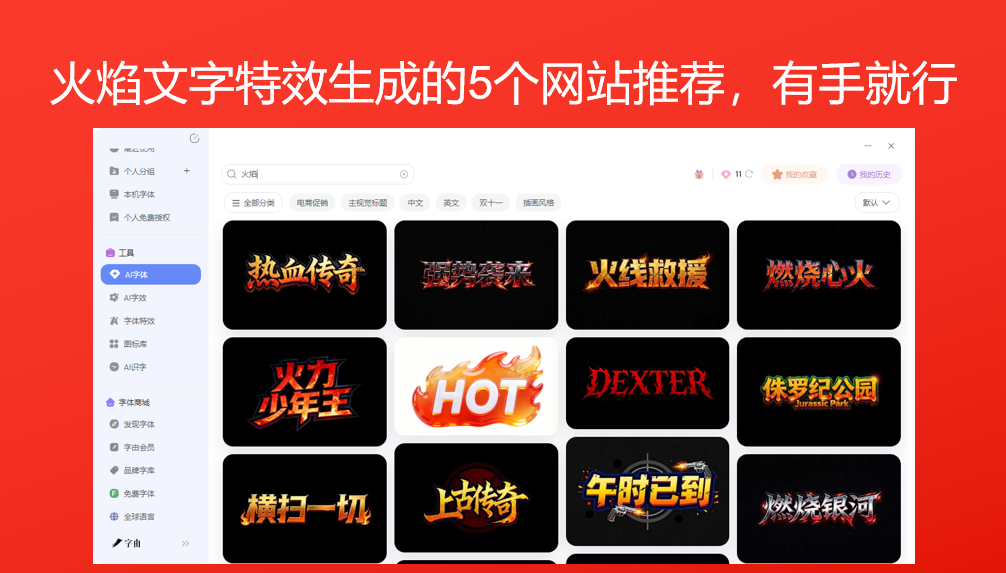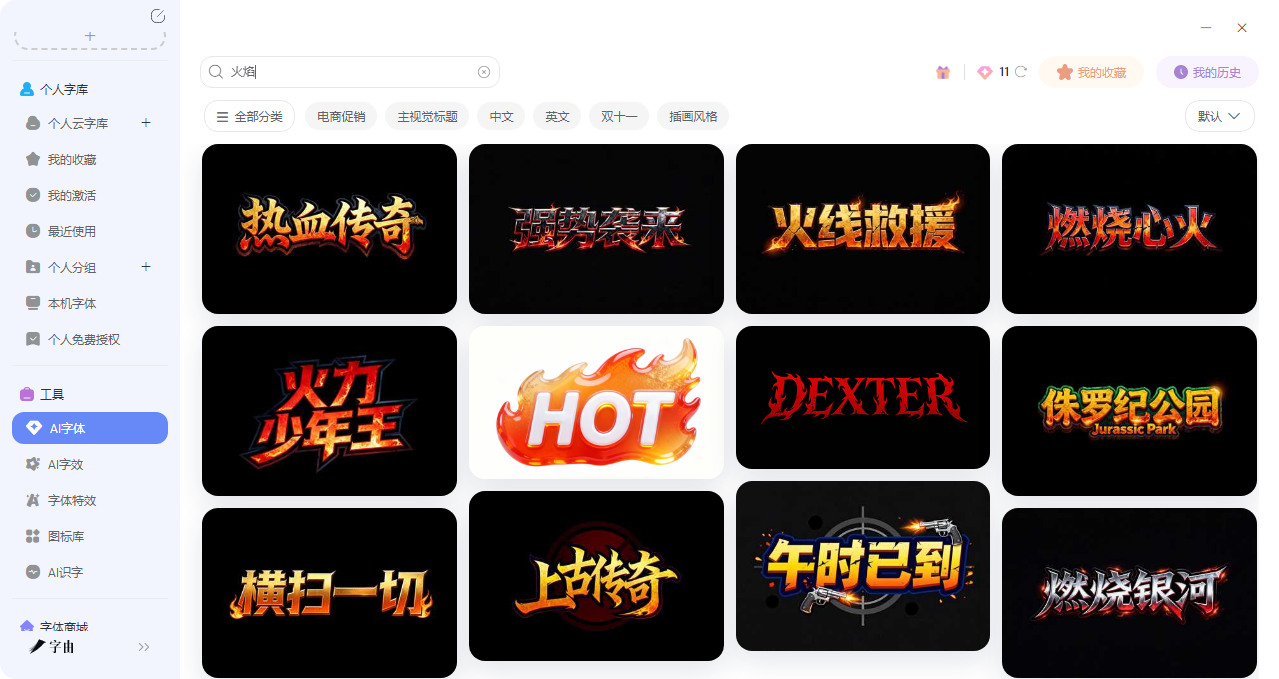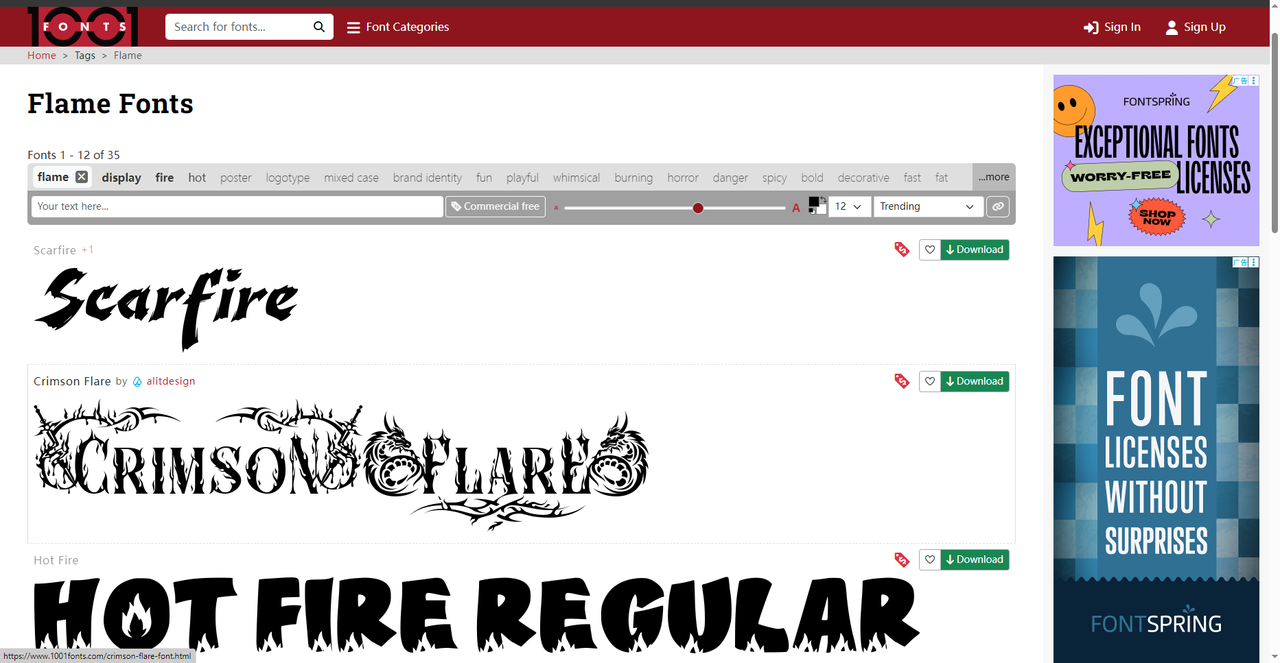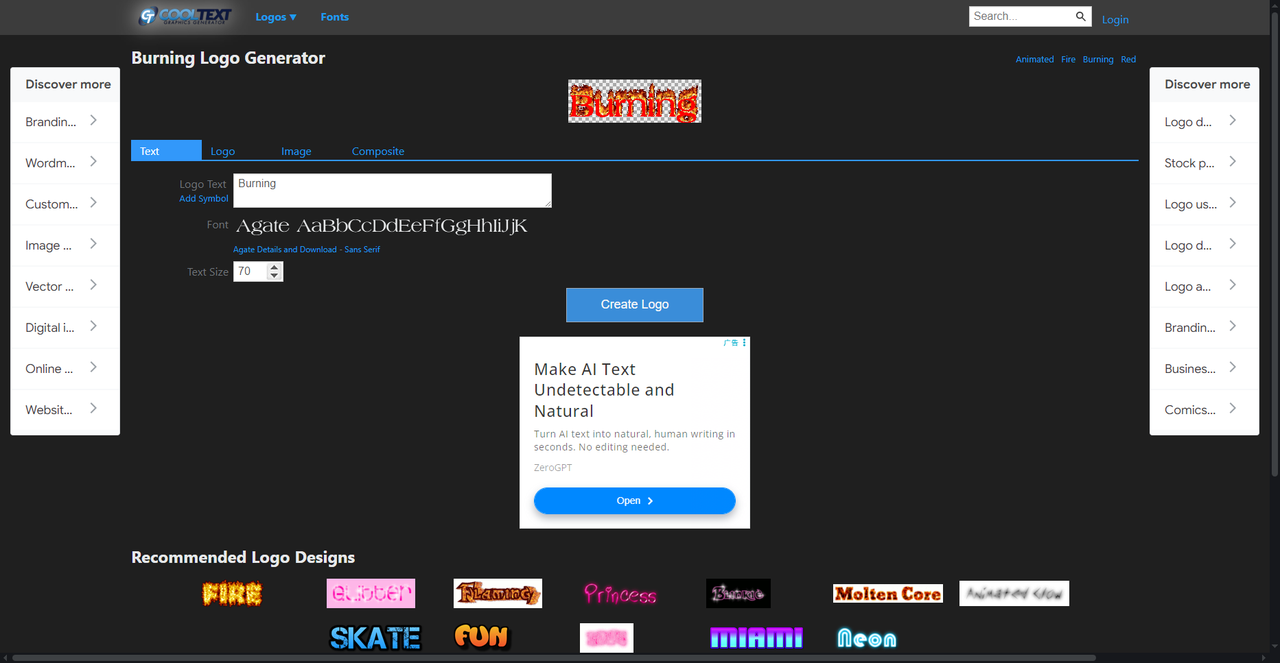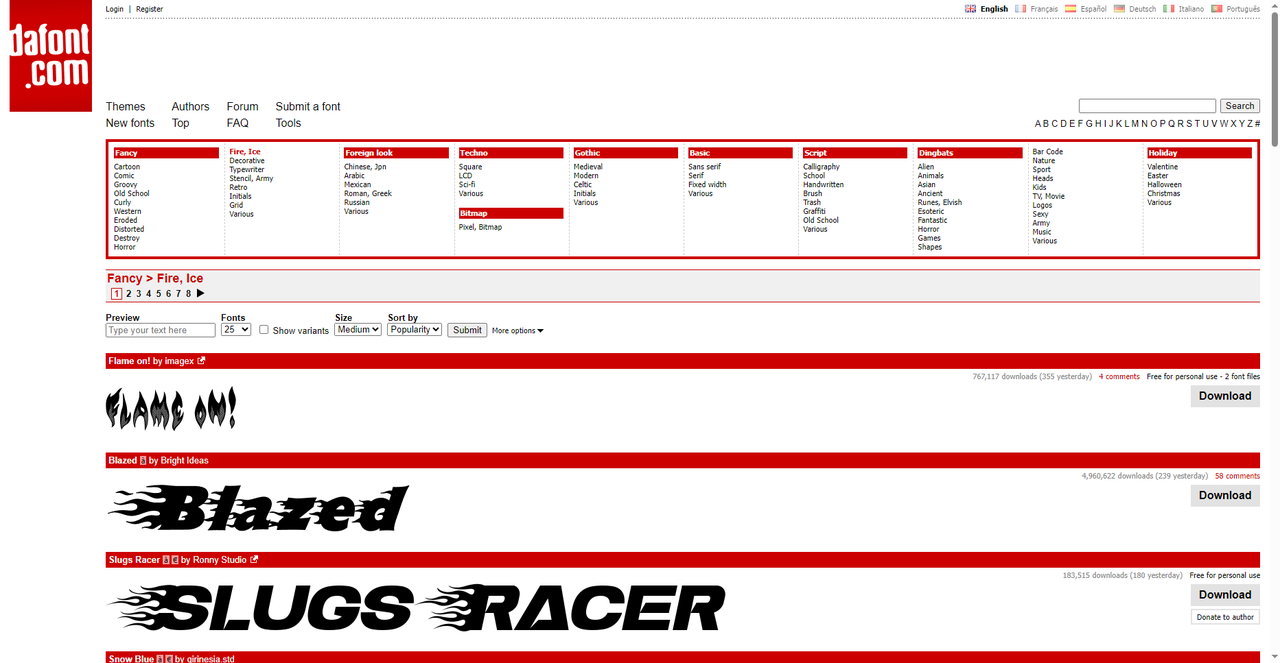
火焰文字特效生成的5个网站推荐,有手就行
相信你肯定在一些电影海报或者是宣传手册上看到过带有火焰特效的文字,真的十分炫酷,心里肯定会想着“这字是怎么做出来的”。如果是我以前的话我肯定会想办法一步一步地把它做出来,就算是复杂也没关系。但是结果基本是耗时又耗力,效果还不一定好。不过现在不一样了,火焰文字特效生成网站可以在几十秒内就完成这件事。那么今天我就筛选了 5 个亲测好用的火焰文字特效生成工具,快来一起看看吧!
第一个要推荐的火焰文字特效生成工具是字由。大家知道字由是个字体库,但它的AI字体功能里藏着不少惊喜,火焰特效就是其中之一。接下来我会给大家介绍如何使用字由来实现快速生成火焰文字:
第一步:打开字由客户端,左侧导航栏找到【工具】→【AI字体】,或者从首页【字体工具】→【AI工具】进入。这个功能内置了大量艺术字模板,从国潮风到科技感,再到我们需要的火焰/燃烧效果,都能找到。
第二步:进入AI字体页面后,在搜索框里输入“火焰”“燃烧”“烈火”“火苗”“火星”等关键词,系统会自动筛选出所有带火焰效果的模板。
第三步:选择喜欢的火焰模板。你可以在搜索结果页面里看到很多火焰字体比如:
• 熊熊烈火效果(火苗往上蹿,动态感强)
• 边缘灼烧效果(文字边缘有烧焦痕迹)
• 火星四溅效果(带飞舞的火星颗粒)
每个模板都有预览图,选一个和你设计风格搭的。
第四步:点击选中的模板,进入编辑页面。在输入框里填你想要生成火焰效果的文字(比如“燃爆全场”“热辣来袭”“火力全开”)。
那么以上就是我要介绍的字由AI 字体如何生成火焰字体的步骤了。如果你还想探索更多的字由AI 工具,可以下载客户端,你就会发现不止AI 工具那么简单。
2、TextStudio
TextStudio 是一个老牌的在线文字特效生成平台,它的火焰字效果非常经典。从图片我们可以看出,它有一个专门的“FLAME”模块。中间的板块清晰地告诉你它的核心功能:
• 实时预览:输入文字后,实时显示火焰效果。
• 参数调节:可以调整字符间距、行高、文字弯曲度、旋转角度等。
• 多种样式:页面底部展示了多种火焰字示例,如“HOT WHEELS”“FREE FIRE”“BURN”等,点击即可应用。
• 矢量下载:支持下载AI/EPS矢量文件,方便后续编辑。
• 动画支持:还能生成动态火焰字(GIF)。
如果说让我找出这个网站唯一的不好的地方也只有它比较老了,界面什么的设计可能有不便之处,再加上还会有广告,所以浏览起来观感不是很好。但是这些都不是重点,TextStudio 的火焰字效果非常逼真,火焰的层次感、颜色过渡都很自然。你甚至可以用它来设计Logo、游戏标题、促销海报。操作简单,不需要任何设计基础。
3、Flame Fonts
这个网站有专门收集火焰字体的板块,目前有35款相关字体。数量虽然不多但是好在足够使用了。不过它的字体谈不上火焰特效,只能说是字体的本身设计效果就带有火焰元素,为什么要把这个网站加进来呢?就是想照顾到有这方面需求的设计师。那我就为大家推荐一下字体:
• Scarfire:由tkzgraphic设计,字体自带燃烧效果,适合热血标题。
• Crimson Flare:红色火焰感,适合危险、警示类设计。
• HOT FIRE REGULAR:直白的火焰字体,笔画像燃烧的木柴。
4、Burning Logo Generator
这个工具是专门用来生成燃烧效果的Logo和文字,尽管如此它也有非常细致的分类:
• Generator Categories:左侧有大量分类,其中“Burning”(燃烧)和“Fire”(火焰)是专门选项。
• 风格多样:除了火焰,还有Glowing(发光)、Neon(霓虹)、Shadow(阴影)等。
• 推荐设计:页面展示了“PRICE”“ELECTRIC”“SKATE”“FUN”等示例,都带有火焰特效。
这个网站的操作也十分简单,只要输入你的文字,点击生成就可以了。
5、DaFont
最后,我想说每一款文字特效都有它独特的魅力所在,无论是促销海报上熊熊燃烧的“限时抢购”,还是游戏标题里滚烫的“热血开战”,几个字就能点燃整个画面的情绪,如果你也想get 到同款字体可以来字由,因为字由对我来说是最顺手的工具,只需要打开客户端,搜“火焰”,选个模板,30秒后就能看到火焰文字的生成了,心动不如行动,快来字由试试吧!